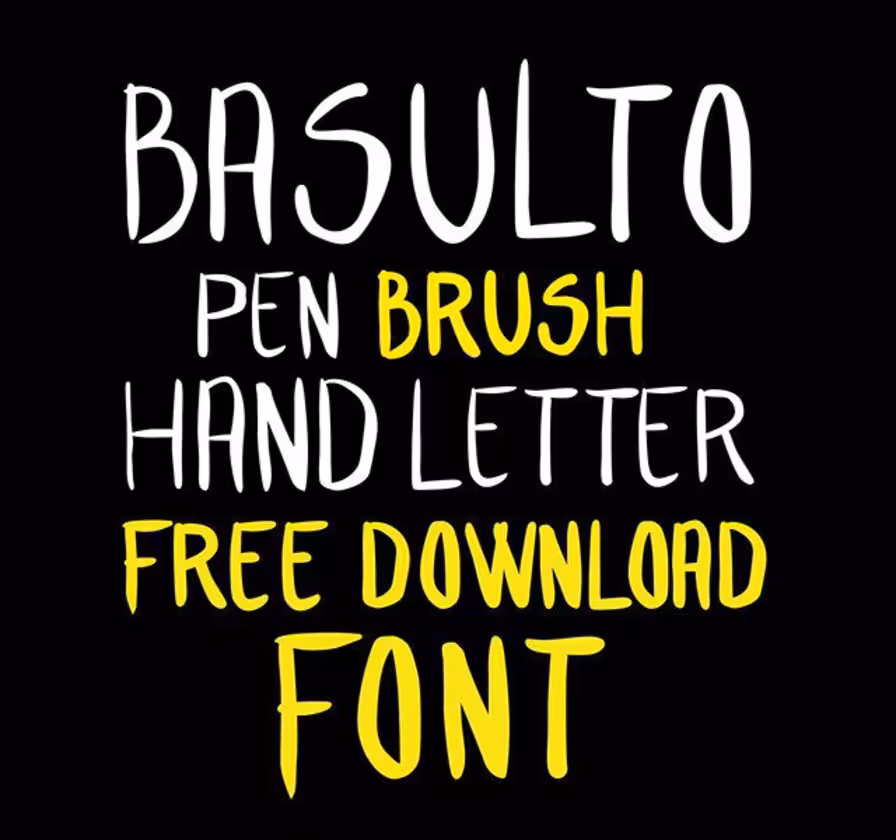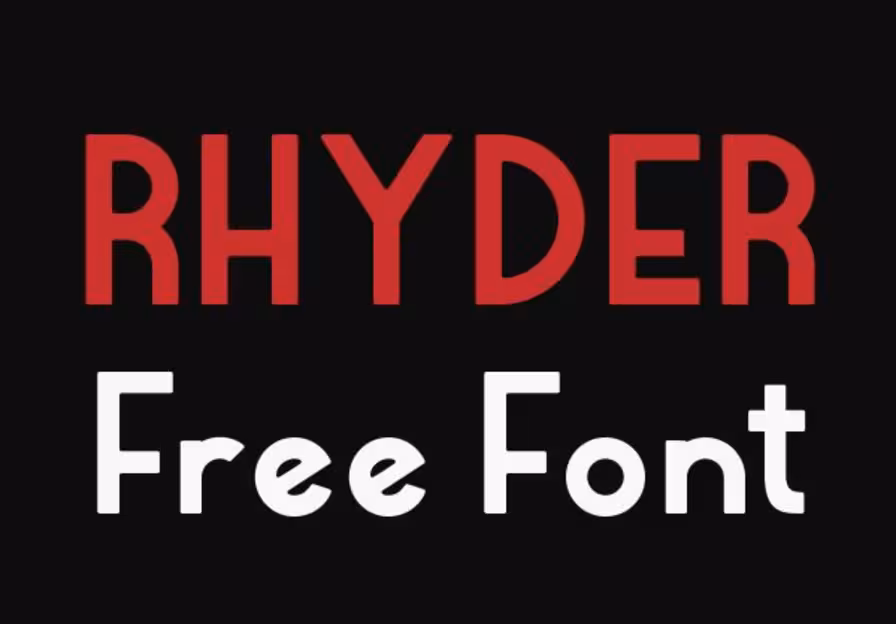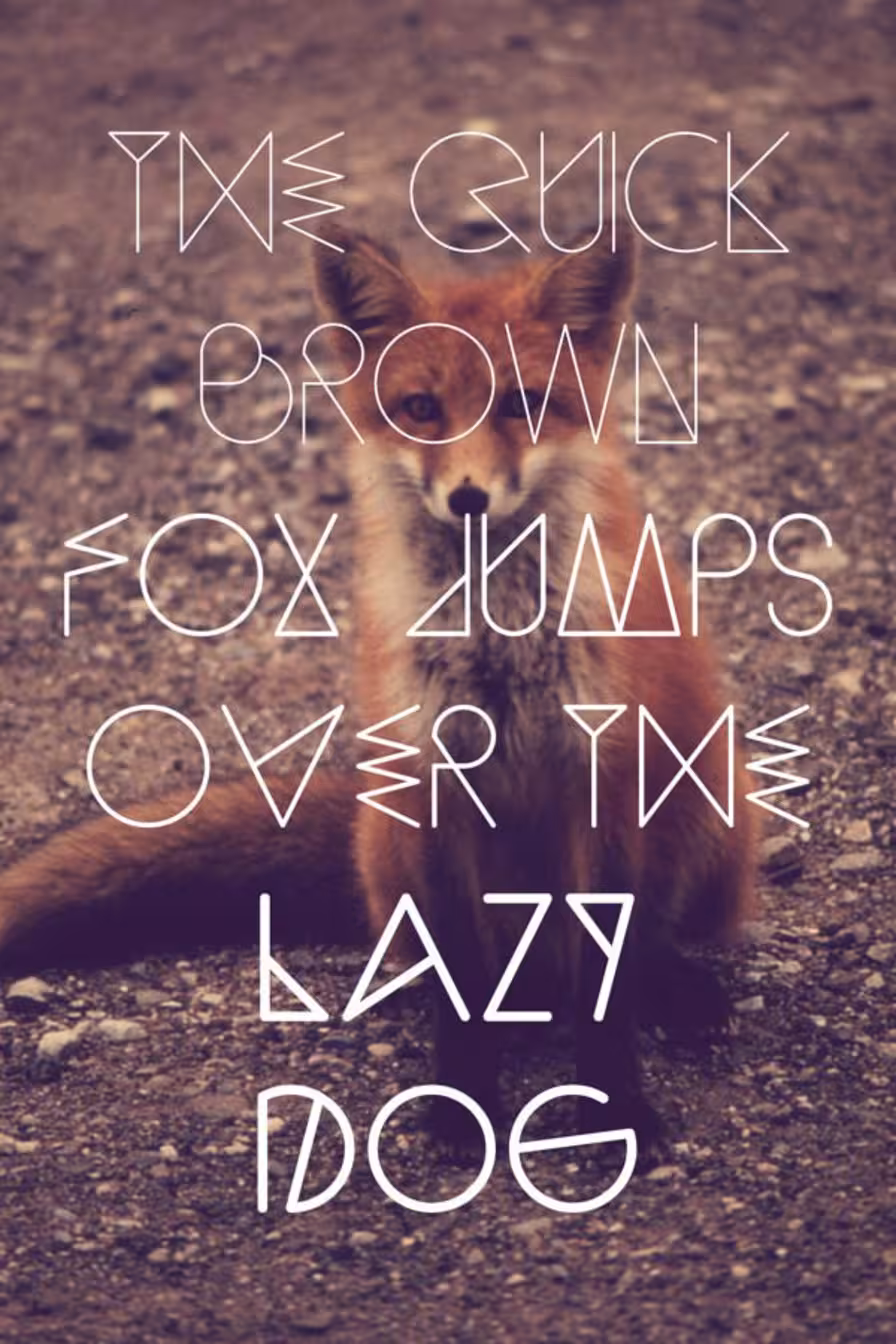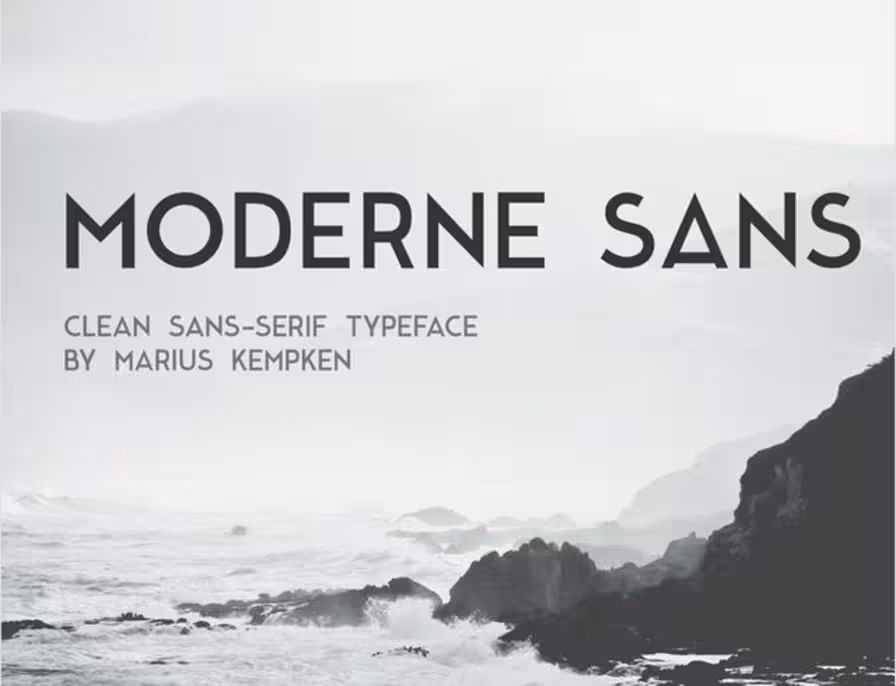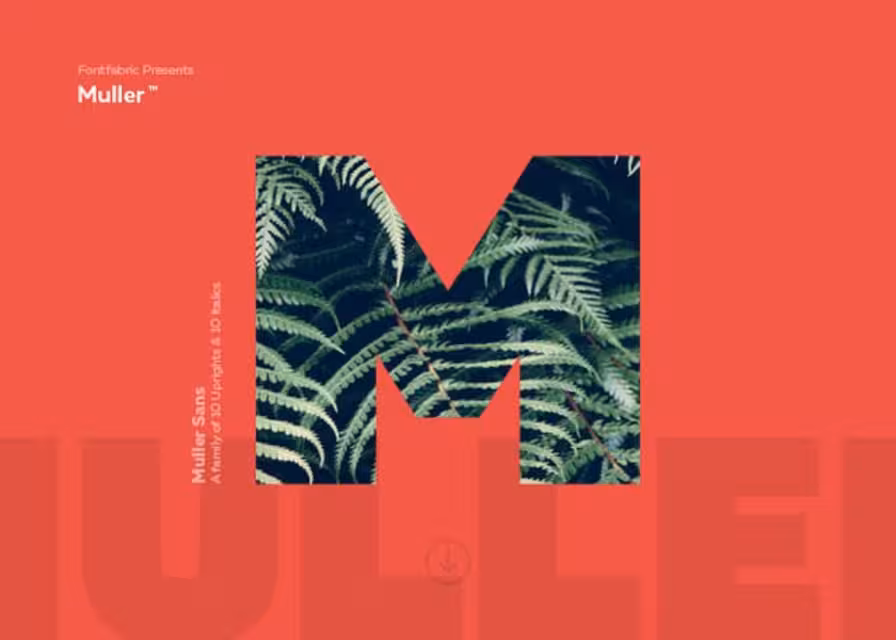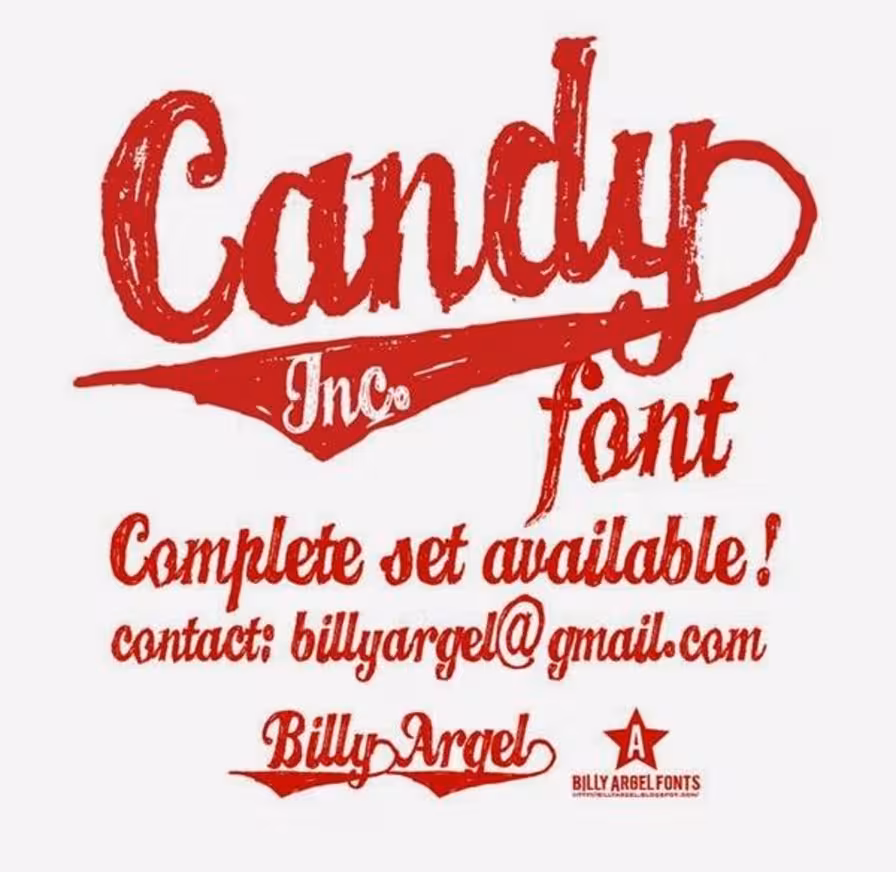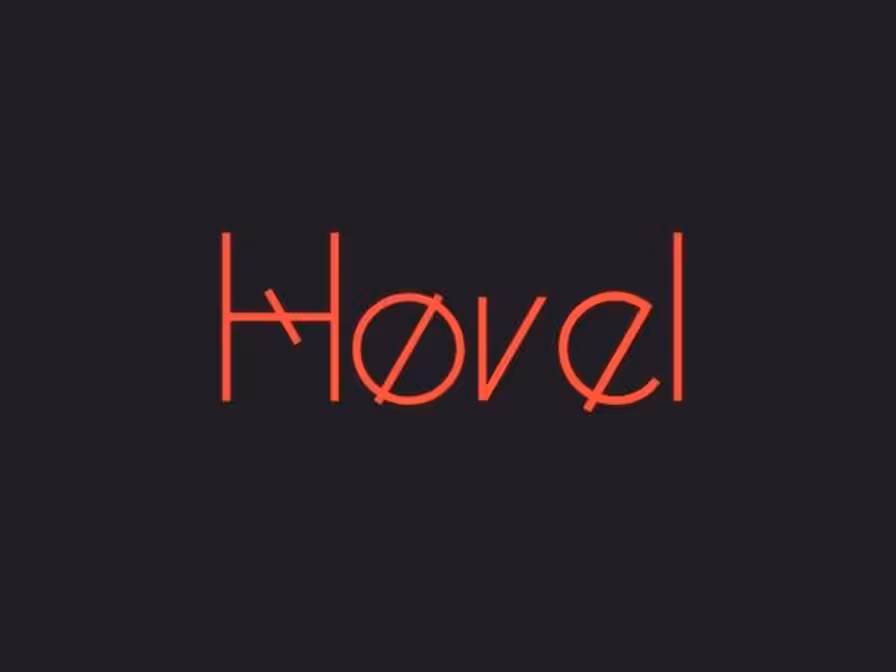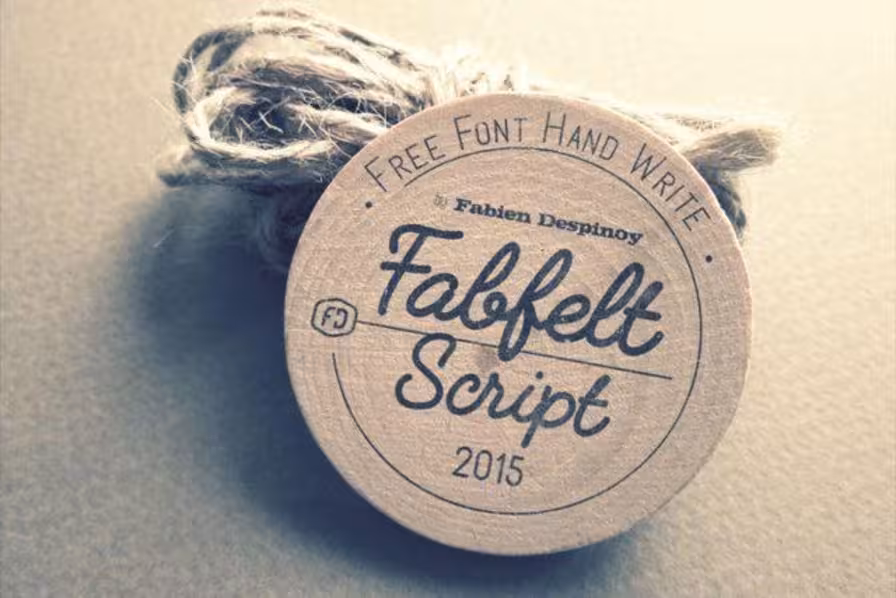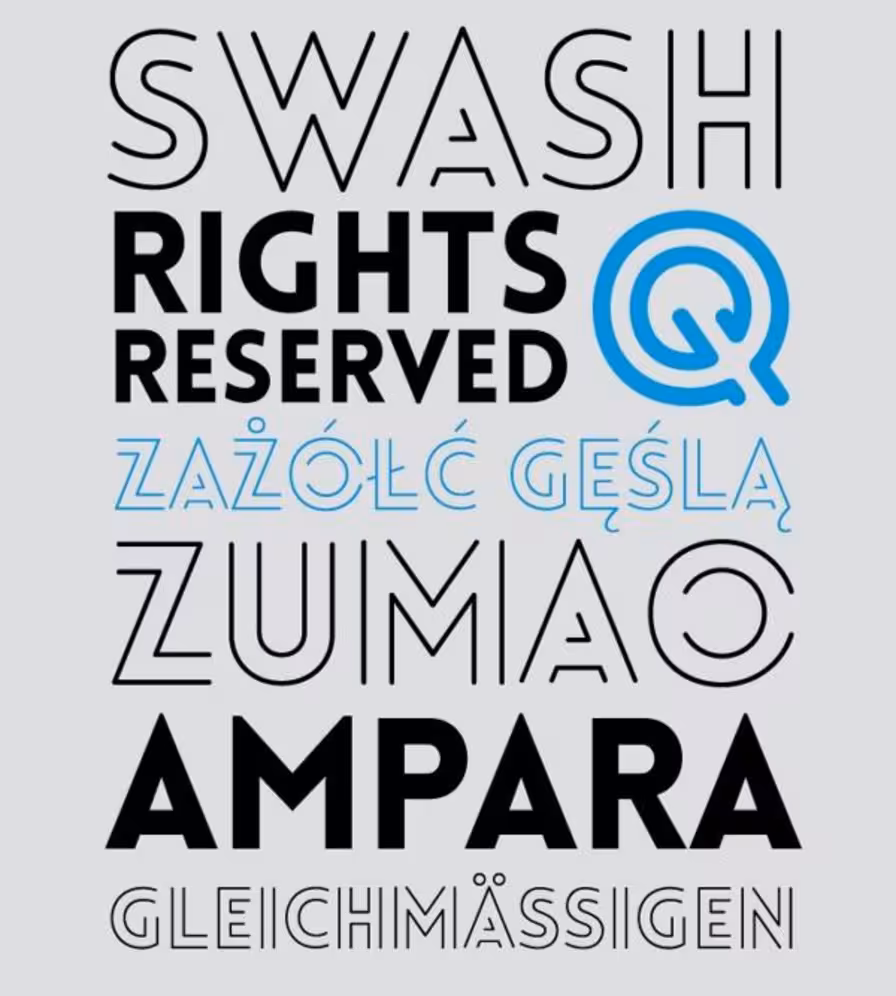
¿Cuáles son las mejores tipografías gratuitas para mi proyecto? Es una pregunta válida que en más de una ocasión nos podemos hacer. Sobre todo sí nos encontramos en la búsqueda de fuentes gratis de alta calidad. Las cuales podamos usar en nuestra herramienta de diseño gráfico favorita.
Por tal motivo, en esta oportunidad he realizado una recopilación de fuentes gratis para descargar. Las cuales de una vez de adelanto que esta colección de tipografías gratuitas. Son ideales para toda clase de proyectos.
Siendo así que tendrá que ver al detalle cada una de estas opciones. Para luego analizar cuál de ellas se ajusta mejor al proyecto en que está trabajando. Aunque ten presente que también podrías descargar cada una de ellas para usar las mismas más adelante.
Como ya he adelantado. En este artículo estaremos viendo los mejores tipos de letra para descargar. Por lo que si buscas: fuentes para logos gratis, fuentes para títulos gratis o tipografías gratis para descargar.
Tipografías gratis para crear anuncios publicitarios.
Buscando tipografías gratis para crear anuncios publicitarios. Encontré cuatro fuentes gratis, las cuales considero son imperdibles para todos aquellos diseñadores gráfico o encargado del área de publicidad.
Que estén buscando crear anuncios publicitarios, físicos o virtuales que sean llamativos y puedan captar la atención de su audiencia.
Asombrosas fuentes tipografías gratuitas.
Como podrá notar, esta colección de fuentes tipografías gratis ofrecen a una gran variedad de líneas y formas. Que van desde las que cuentan con un diseño vintage, hasta las que ofrecen un diseño moderno que permite usarlas en afiches, volantes y demás.
Descargar fuentes gratis para afiches.
Llegado a este punto voy a presentar cuatro tipografías gratis que considero perfectas para la creación de afiches publicitarios. Que dicho sea de paso se pueden hacer fácilmente con herramientas tan potentes como Adobe Photoshop o Canva.
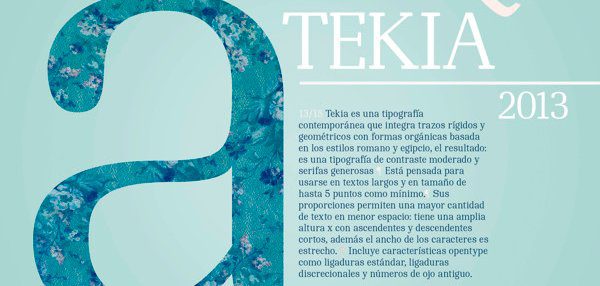
Fuentes gratis de alta calidad con un diseño interesante.
Como podrás notar a continuación, estas fuentes son una buena opción para la publicidad en general. Ya que ellas presentan un diseño fresco y moderno. Que se adapta muy bien en el campo del marketing digital.
Por favor, ten presente que también puedes usar estas tipografías gratuitas para la elaboración del material del ministerio juvenil. Pudiendo emplear las mismas tanto en la portada como en los encabezados.
Fuentes para logos gratis para el diseño gráfico.
Las cuatro fuentes para logos gratis que te voy a presentar en esta parte son realmente increíbles. Ya que nos sacan de la rutina de siempre utilizar las mismas tipografías.
Desde luego, llegado a este punto tienes una gran cantidad de tipografías gratis para logos. Pero como ya te adelantaba, lo que me gustan de las siguientes cuatro fuentes gratis. Es que son un tanto diferentes al resto.
Por cierto, siempre recomiendo que antes de usar la fuente en cualquier tipo de proyecto. Lea detenidamente la licencia de uso de cada tipografía antes de utilizarla. Ya que si bien todas son gratis. Algunas pueden llegar a tener restricciones para el empleo comercial.
Fuentes para títulos gratis con diseño industrial.
En caso de que esté buscando tipografías gratis de alta calidad gratis con diseño industrial. Puede acudir a las siguientes cinco fuentes gratis online. Las cuales solo necesita descargar en su ordenador para luego copiar y pegar en la carpeta de fuentes.
¡Interesante verdad! Sin lugar a dudas una buena guía para todos aquellos que nos somos diseñadores gráficos.
Conclusión de las mejores tipografías gratuitas.
¿Qué te ha parecido esta colección de tipografías gratuitas? Espero que te hayan encantado y que estés listo para incluir las mismas como parte de tus tipografías favoritas para este año.